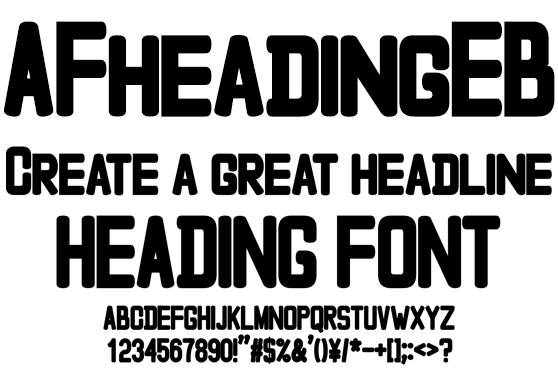
見出し専用 AFheadingEB
AFheadingEB
ファッション系ドキュメント、サムネイルに最適な大見出し専用太字欧文です。角に施された柔らかめなカーブが優しさを醸しだしながらも、キーワードを強調します。Web Serverへのアップロード、フォント共有サーバー利用、PDF エンベッド、印刷やロゴなど作成と登録、印影や彫刻、画像化後ソフトへのバンドルなど商用利用できます。